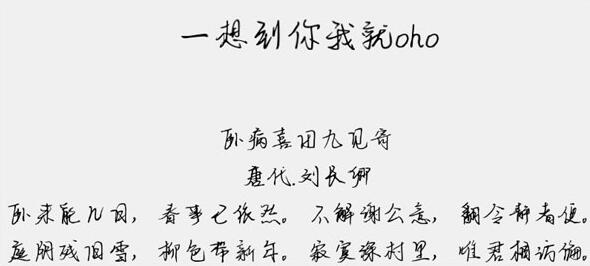
一想到你我就oho是一款十分好用,且非常漂亮的艺术字体,同时也是由文道字库倾情发布,字体在字与字之间有着一种行云流水的畅意,无论是笔法的撇捺伸张还是字形的灵动飘逸,都能给用户极为舒适的感觉,适应于报纸和杂志和书籍中常用字体, 海报、个性促进品牌标志设计、文本装潢、信息展示、篆刻制模英文、数据制作、装潢设计、视觉设计、字帖等一切合法应用场景,有喜欢的朋友可免费下载收藏。